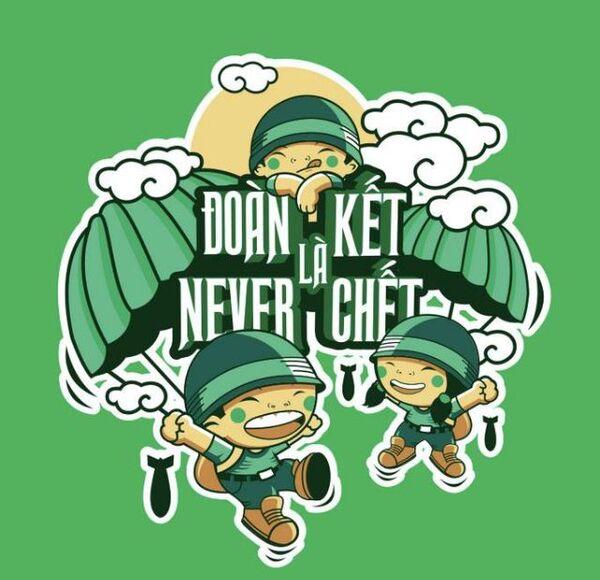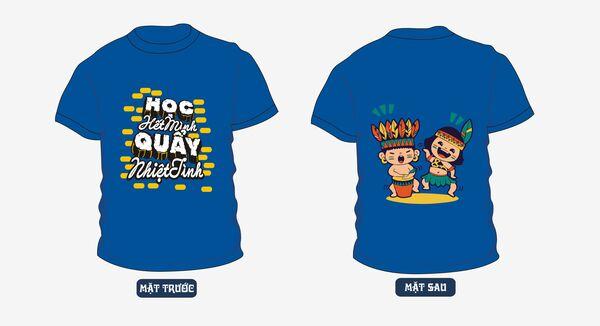
Mặc áo lớp, áo đội nhóm là một hình thức thể hiện văn hóa, tinh thần đoàn kết của tập thể. Font chữ là một yếu tố quan trọng giúp tạo điểm nhấn cho chiếc áo. Cùng Coolmate đi tìm 04 font chữ in áo chất và phổ biến nhé.
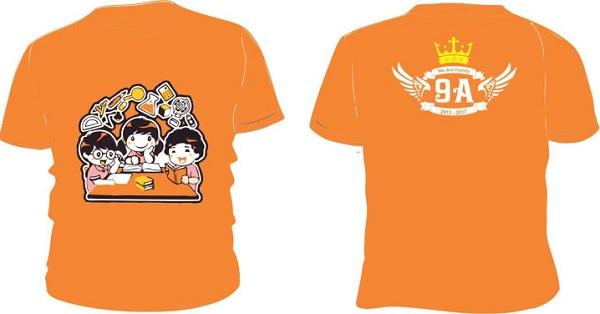
Font chữ in áo chất
1. 06 lưu ý khi thiết kế font chữ in áo
1.1. Dễ đọc
Khi chọn font chữ in áo, điều quan trọng và cần lưu ý là tính dễ đọc. Phải đảm bảo rằng kể cả khi người khác đứng từ xa, trong một khoảng cách định thì họ cũng có thể đọc dòng chữ in trên chiếc áo thun họa tiết của bạn.
1.2. Tính cảm xúc
Font chữ có khả năng truyền đạt một loạt các thông điệp và cảm xúc. Vì vậy, việc chọn đúng font chữ là điều cực kỳ quan trọng. Khi nhìn các font chữ, chúng ta có thể liên tưởng đến sự vui tươi, sợ hãi, mộc mạc hay sạch sẽ…
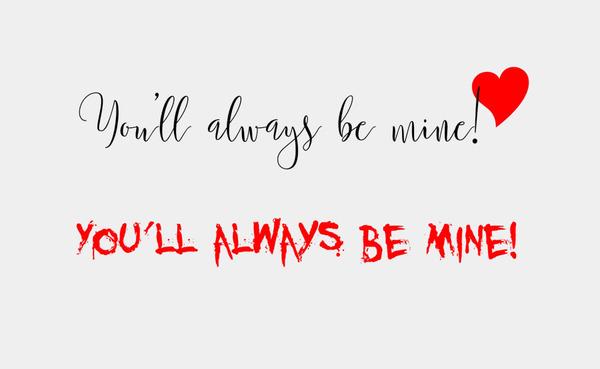
Cùng một nội dung nhưng khác ý nghĩa
1.3. Phù hợp chủ đề
Font chữ in áo phải được sử dụng phù hợp với mục đích và hoàn cảnh. Nếu áo được mặc trong những dịp quan trọng thì kiểu chữ in áo cũng cần thể hiện sự nghiêm túc. Ngược lại, nếu là áo mặc đi chơi thì nên font chữ kiểu vui nhộn.
1.4. Kiểu chữ và định dạng chữ
Mỗi kiểu chữ (typeface) lại có rất nhiều định dạng (font) khác nhau, mô tả độ dày, mỏng và độ nghiêng của chữ.
Ví dụ, cùng một kiểu chữ Roboto nhưng lại có nhiều định dạng như:
Roboto Thin (Mảnh)
Roboto Light (Nhẹ)
Roboto Regular (Thường)
Roboto Medium (Trung bình)
Roboto Bold (In đậm)
Roboto Black (Đen)
Các font chữ dày và đậm thường phù hợp sử dụng cho thiết kế logo nhưng chúng sẽ trông “chật chội” và “cồng kềnh” khi áp dụng cho các slogan dài.
Thiết kế logo thường sử dụng font dày và đậm
Tương tự như vậy, các font chữ mảnh và nhẹ sẽ phù hợp khi thiết kế danh thiếp, thiệp mời nhưng chúng sẽ “mất tác dụng” cho áo thun đồng phục, đặc biệt là khi nhìn từ xa.
Việc cần làm chính ở đây là thử xem font chữ áo phông của bạn sẽ trông như thế nào trong thực tế, tránh việc dùng font tùy ý.
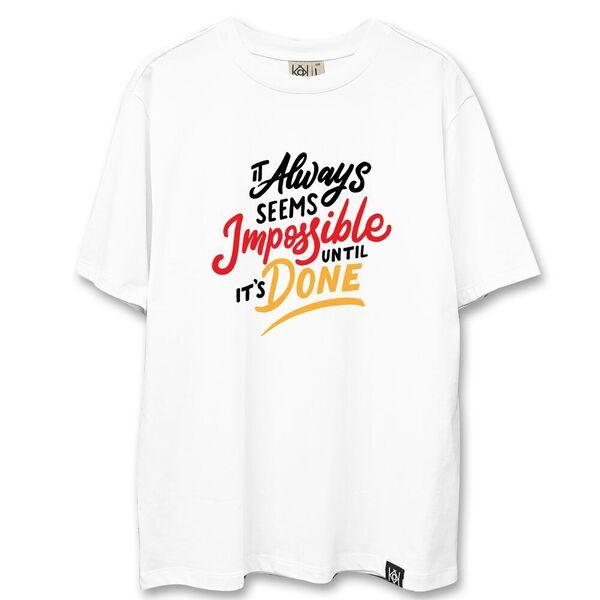
Kiểu chữ in áo chất
1.5. Giới hạn số lượng font chữ
Cố gắng không kết hợp nhiều hơn hai phông chữ trong một thiết kế. Tốt chỉ chọn một.
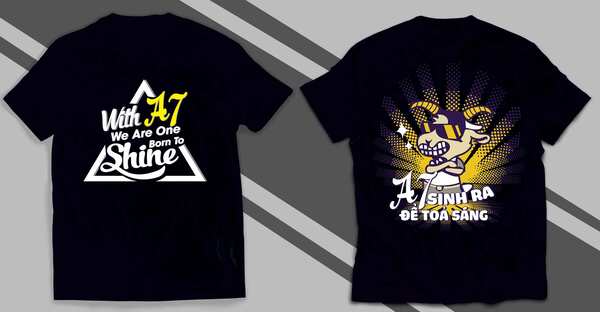
Không nên sử dụng quá nhiều font chữ
2. Tổng hợp 04 font chữ in áo chất và phổ biến
2.1. Font Bohema
Bohema là font chữ mang nét đẹp “lai” giữa truyền thống và hiện đại. Font chữ này thường được sử dụng trong các bài báo, tiêu đề hay để in áo lớp, đồng phục trường học,…
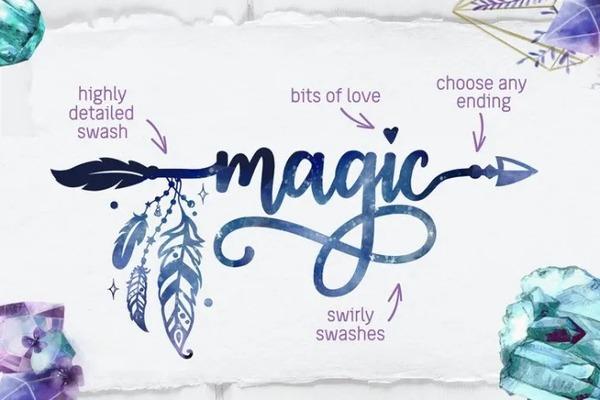
Font chữ Bohema
2.2. Font UVF Chikita
Được đánh giá cao về tính thẩm mỹ, UVF Chikita là font chữ bạn nên tham khảo khi có ý định in áo theo yêu cầu.
2.3. Font La Sonnambula
Là một font viết tay với những đường nét mềm mại, tinh tế, font La Sonnambula sẽ tôn lên vẻ đẹp của chiếc áo in.
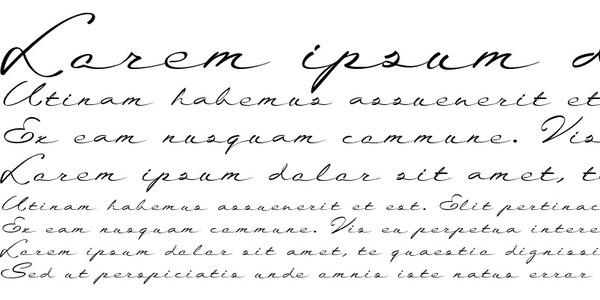
Font La Sonnambula
2.4. Cider
Cider là kiểu font chữ nghiêng với đường nét uốn lượn, mang đến sự bay bổng, lãng mạn. Kiểu font này đặc biệt phù hợp để thiết kế slogan áo lớp theo phong cách dễ thương, ngộ nghĩnh. Đây cũng là kiểu font thích hợp để in áo câu lạc bộ nghệ thuật hay lớp chuyên văn…
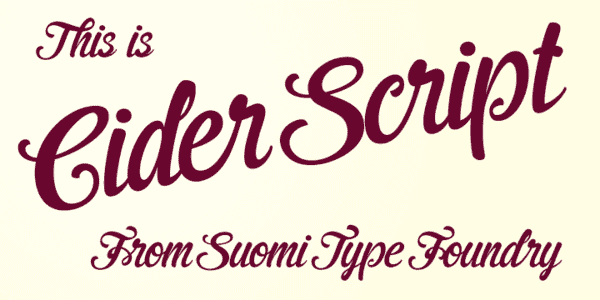
Font Cider